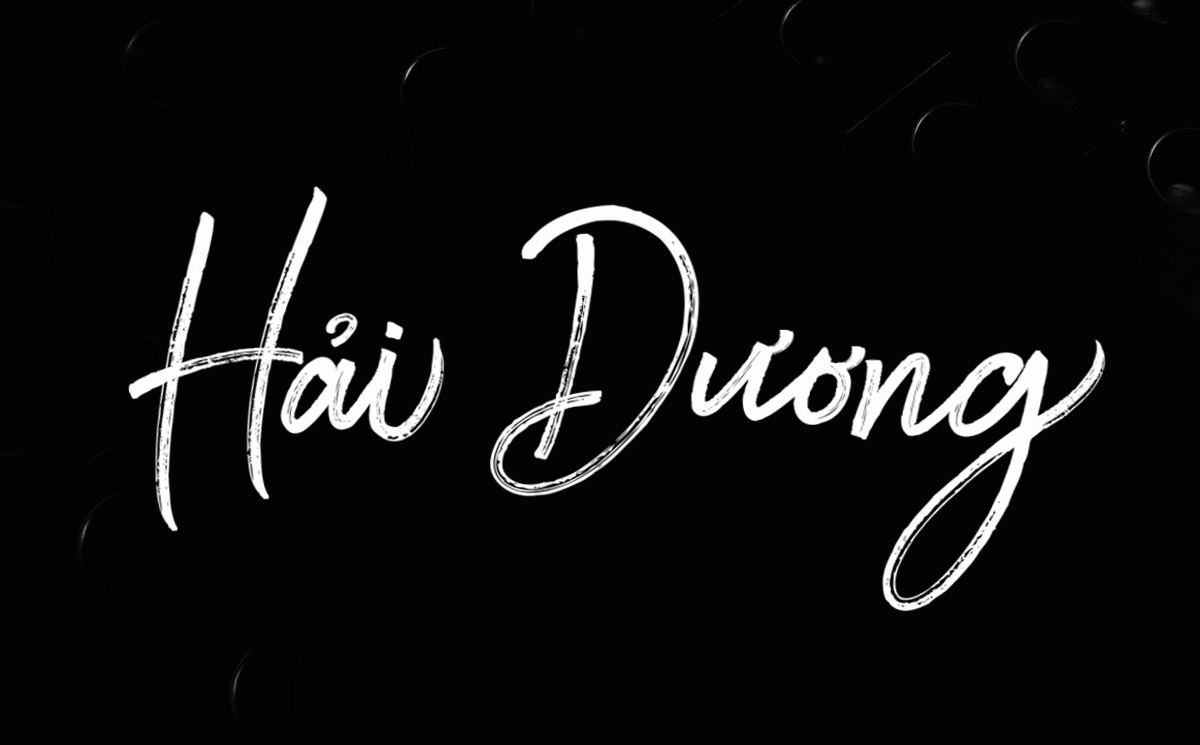
Font chữ viết tay, chữ ký mềm mại cho thiệp cưới, đám cưới SVN-Brownhill Script
Thiệp cưới không chỉ đơn thuần là một lời mời mà còn là tác phẩm nghệ thuật đầu tiên đánh dấu mốc kỷ niệm trọng đại trong cuộc đời của mỗi cặp đôi. Để tạo nên một mẫu thiệp cưới sang trọng, ấn tượng và đong đầy cảm xúc, việc lựa chọn font chữ đóng vai trò vô cùng quan trọng. SVN-Brownhill Script chính là font chữ viết tay, chữ ký mềm mại đỉnh cao dành riêng cho thiết kế thiệp cưới, giúp nâng tầm vẻ đẹp tinh tế và đẳng cấp cho ngày vui của bạn.
Khám Phá Vẻ Đẹp Tinh Tế Của Font Chữ Viết Tay, Chữ Ký Mềm Mại Cho Thiệp Cưới, Đám Cưới SVN-Brownhill Script
SVN-Brownhill Script là bộ font chữ được thiết kế theo phong cách thư pháp hiện đại (Modern Calligraphy) kết hợp với kiểu chữ ký nghệ thuật (Signature Script). Sự hòa quyện giữa các đường nét thanh đậm nhịp nhàng, uốn lượn tự nhiên đã mang lại cho bộ font này một sức hút kỳ diệu. Không cứng nhắc như những font chữ in hoa truyền thống, SVN-Brownhill Script đem đến cảm giác chân thật, ấm áp như chính tay cô dâu chú rể đang nắn nót viết từng dòng chữ gửi tới quan khách.</p>
1. Đường nét uốn lượn mềm mại và phong cách chữ ký tự nhiên
Điểm đặc biệt nhất của SVN-Brownhill Script nằm ở cấu trúc nét chữ vô cùng linh hoạt. Các nét móc, nét uốn được chăm chút tỉ mỉ để tạo ra độ tự nhiên tối đa, mô phỏng hoàn hảo nét bút mực thủ công trên chất liệu giấy cao cấp.
• Nét thanh nét đậm tự nhiên: Sự chuyển đổi nhịp nhàng giữa nét nhấn và nét nhả giúp từ ngữ trở nên sinh động, không bị thô cứng hay gượng gạo.
• Tính thẩm mỹ cao: Rất phù hợp để thể hiện tên cô dâu chú rể (Bride & Groom Names), tạo nên điểm nhấn thị giác cuốn hút ngay từ ánh nhìn đầu tiên.
• Phong cách chữ ký (Signature Style): Mang đến cảm giác cá nhân hóa độc bản, thể hiện sự trân trọng và chỉn chu của gia chủ đối với từng vị khách mời.
2. Bộ ký tự Việt hóa hoàn chỉnh (SVN) hỗ trợ đầy đủ dấu tiếng Việt
Một trong những thách thức lớn nhất khi sử dụng các font chữ script quốc tế là vấn đề lỗi font khi gõ tiếng Việt. SVN-Brownhill Script đã được Việt hóa chỉn chu và chuẩn hóa toàn bộ hệ thống dấu câu, đảm bảo giữ trọn nét đẹp thẩm mỹ mà không lo rách nét hay lỗi ký tự.
Bộ dấu tiếng Việt trong SVN-Brownhill Script được tinh chỉnh vị trí một cách khéo léo để không làm đứt gãy sự liên kết giữa các chữ cái. Dù bạn viết tên riêng, câu đối, lời mời hay các đoạn thơ tình yêu dài, font chữ vẫn giữ được sự mượt mà, đồng điệu và cực kỳ dễ đọc.
3. Bảng Glyph phong phú với hệ thống Swash và Alt Glyphs độc đáo
SVN-Brownhill Script sở hữu một kho tàng ký tự thay thế (Glyphs) vô cùng phong phú, cho phép các nhà thiết kế tự do sáng tạo và biến hóa theo nhiều phong cách khác nhau.
• Nét gạch chân và đuôi chữ trang trí (Swashes): Cung cấp nhiều đường uốn lượn nghệ thuật ở đầu và cuối từ, tạo hiệu ứng chữ ký bay bổng đầy kiêu sa.
• Ký tự nối ngẫu nhiên (Ligatures): Tự động kết nối các chữ cái một cách thông minh, giúp khoảng cách giữa các chữ tự nhiên như nét chữ viết tay thực tế.
• Chữ cái thay thế (Alt Glyphs): Giúp bạn dễ dàng thay đổi kiểu dáng của các chữ cái viết hoa hoặc viết thường để tránh sự lặp lại đơn điệu trong cùng một dòng văn bản.
4. Ứng dụng hoàn hảo cho thiết kế thiệp cưới và ấn phẩm sự kiện
Không chỉ dừng lại ở thiệp mời, SVN-Brownhill Script là giải pháp typography toàn diện cho toàn bộ hệ thống nhận diện của một đám cưới hiện đại cũng như các sự kiện cao cấp.
1. Thiệp mời cưới (Wedding Invitations): Làm nổi bật tên cô dâu, chú rể và tiêu đề “Thiệp Mời” với phong cách sang trọng, cổ điển pha lẫn hiện đại.
2. Bảng đón khách (Welcome Board): Tạo điểm nhấn ấn tượng ngay tại sảnh tiệc, thể hiện gu thẩm mỹ tinh tế của cặp đôi.
3. Thực đơn tiệc cưới (Wedding Menu) & Card cảm ơn (Thank You Card): Giúp từng chi tiết nhỏ nhất trong buổi tiệc đều nhất quán và đong đầy tình cảm.
4. Stamp logo & Khắc tên: Rất phù hợp để làm con dấu sáp (Wax Seal), khắc laser trên gỗ, acrylic hoặc in ép kim nổi trên bìa thiệp.
5. Khả năng tương thích linh hoạt trên mọi phần mềm thiết kế
SVN-Brownhill Script được đóng gói ở định dạng chuẩn (OTF/TTF), mang lại sự tiện lợi tuyệt đối cho cả nhà thiết kế chuyên nghiệp lẫn người dùng cá nhân.
Font chữ tương thích hoàn hảo với các phần mềm đồ họa hàng đầu như Adobe Photoshop, Adobe Illustrator, Adobe InDesign, CorelDraw. Đặc biệt, font cũng hoạt động mượt mà trên các công cụ trực tuyến phổ biến như Canva, Procreate trên iPad, cũng như các ứng dụng văn phòng Microsoft Word, PowerPoint mà không gặp bất kỳ sự cố hiển thị nào.
Bí Quyết Phối Font SVN-Brownhill Script Để Có Mẫu Thiệp Cưới Đẹp Chuẩn Xu Hướng
Để tận dụng tối đa vẻ đẹp của font chữ viết tay, chữ ký mềm mại SVN-Brownhill Script trong thiết kế thiệp cưới, bạn nên áp dụng một số nguyên tắc phối chữ (Font Pairing) đỉnh cao dưới đây:
5. Kết hợp với Font Sans-serif (Chữ không chân thanh lịch): Sử dụng SVN-Brownhill Script cho phần tên riêng và tiêu đề chính, kết hợp với một font Sans-serif hiện đại, rõ ràng cho phần thông tin ngày tháng, địa điểm để đảm bảo tính dễ đọc.